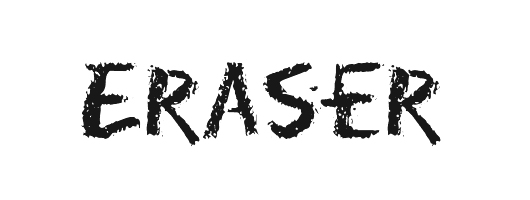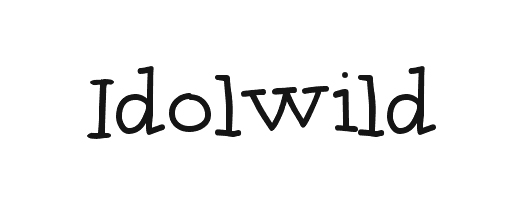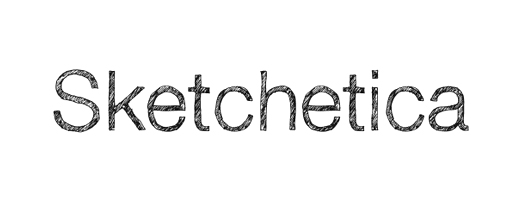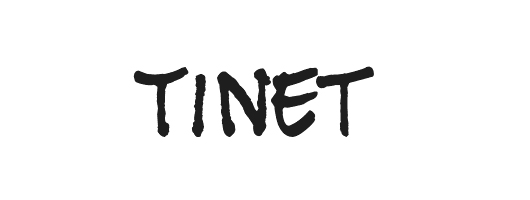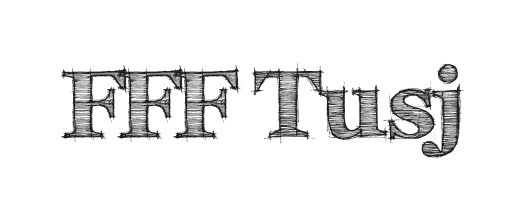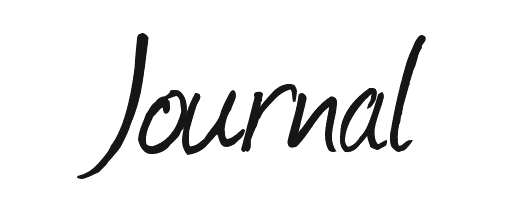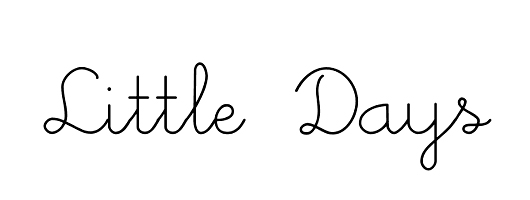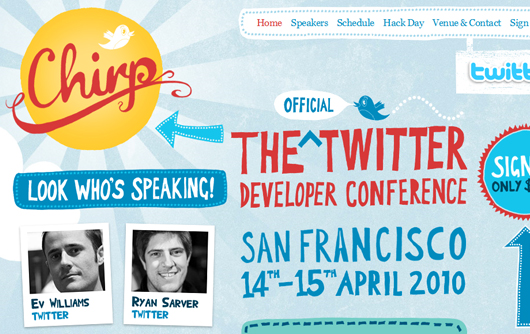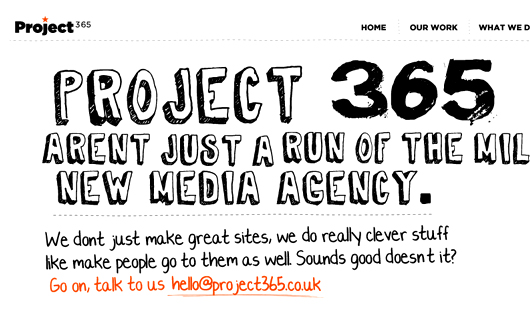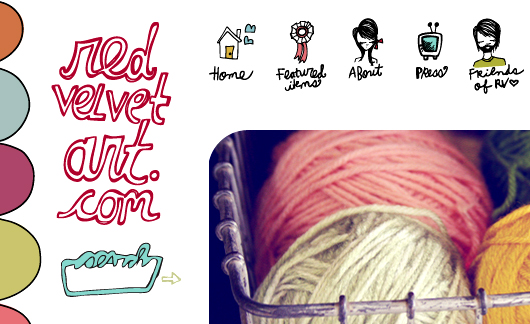
Selbst ist der Webdesigner, oder zumindest fast ;-) Denn jede Menge wunderschöne Schriften im Handmade-Style kannst du dir auf FreeFont-Portalen wie dafont.com oder Fontsquirrel kostenlos herunterladen. Hier meine Lieblingsauswahl an Skizzen- und Scribblefonts! Go get creative ;-)
1. Eraser
2. Idolwild
3. Sketchetica
4. Tinet
5. FFF Tusj
6. Journal
7. Little Days
8. Hand Test
9. Honey I stole your Font
10. Gorillaz
11. Sketchy Times
12. Mia’s Scribbling
13. Simon Script
14. Coert Schrift
15. April 16
16. Rodeo King
17. Rai
18. Brushed
19. Sketch Block
20. WC Roughtrad
Handmade Fonts im Einsatz
Und hier noch ein paar Inspirationsquellen, was sich mit Handmade-Schriften so alles anstellen lässt.